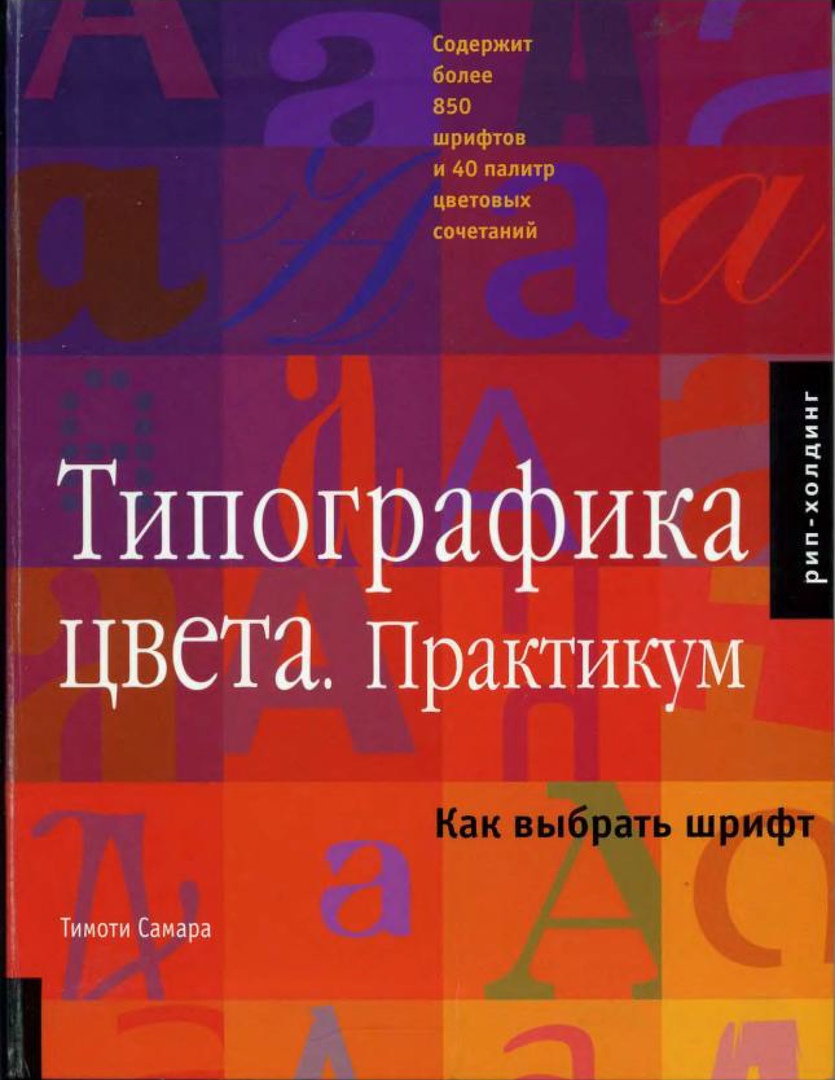
«Типографика цвета. Практикум. Как выбрать шрифт», Тимоти Самара
Этот красочный том – простой способ выбрать нужный шрифт и цвет. Небольшой экскурс в историю шрифта предваряет четыре основных раздела: настроение, концепция, исторический период, возрастные группы. Книга помогает читателю подобрать наиболее подходящий шрифт и цветовую комбинацию, соответствующую определенной теме или настроению. “Типографика цвета. Практикум” – это каталог шрифтов, который должен стать настольной книгой каждого дизайнера.